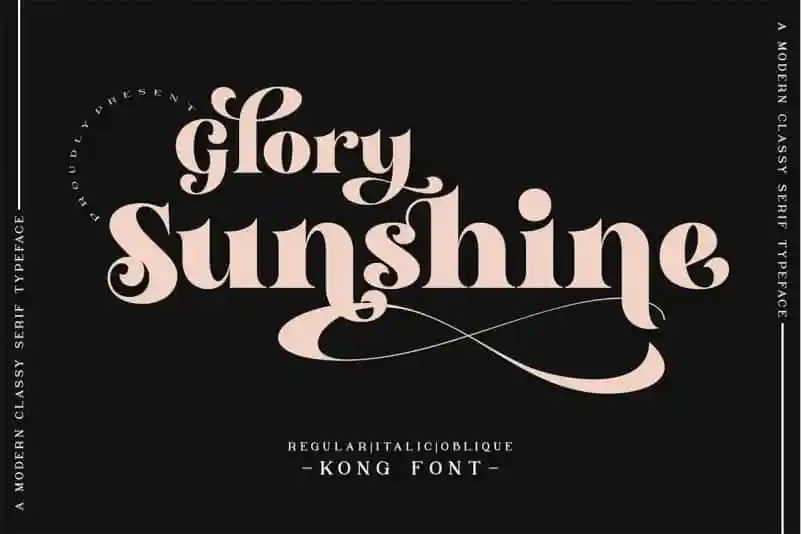
Glory Sunshine Serif Font – Download Grátis
A Glory Sunshine Serif Font é uma tipografia serif display que carrega uma aparência nostálgica moderna. Desenvolvida pelo font designer fontkong, foi concebida com a ideia de incorporar elementos das mais audaciosas linhas do luxo contemporâneo em seu design. O resultado é uma fonte suave e versátil, projetada para facilitar o uso através da integração de alternativas estilísticas e ligaturas disponíveis no OpenType. Embora seja uma tipografia serif, Glory Sunshine parece ter sido criada sob a inspiração da moda contemporânea extravagante. Suas linhas elegantes e delicadas são um excelente complemento para qualquer design que busque uma combinação de modernidade sofisticada e história clássica. Com sua simplicidade cuidadosamente projetada, este é mais que uma fonte de luxo; ele é uma ferramenta ideal para quem busca expressar elegância e sofisticação em seus trabalhos gráficos contemporâneos. Esta fonte, disponível na categoria de serif fonts pelo 99designs, oferece um toque único que pode transformar qualquer projeto gráfico. Seja para a criação de materiais publicitários, editoriais ou até mesmo o design de aplicativos móveis, Glory Sunshine Serif Font é uma escolha perfeita para quem busca tanto simplicidade quanto profundidade em seu trabalho visual.